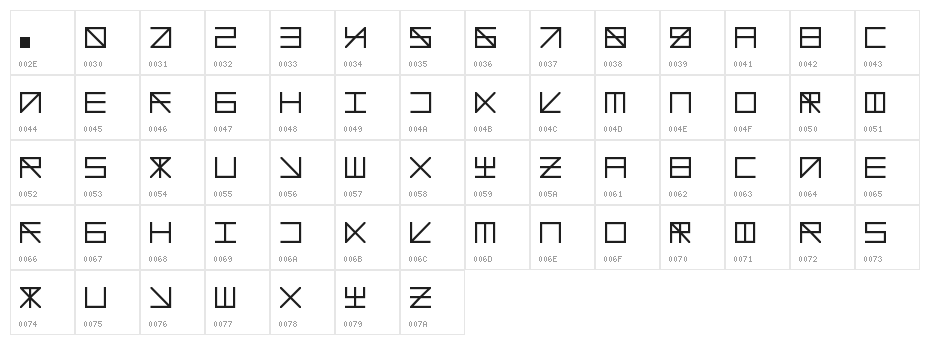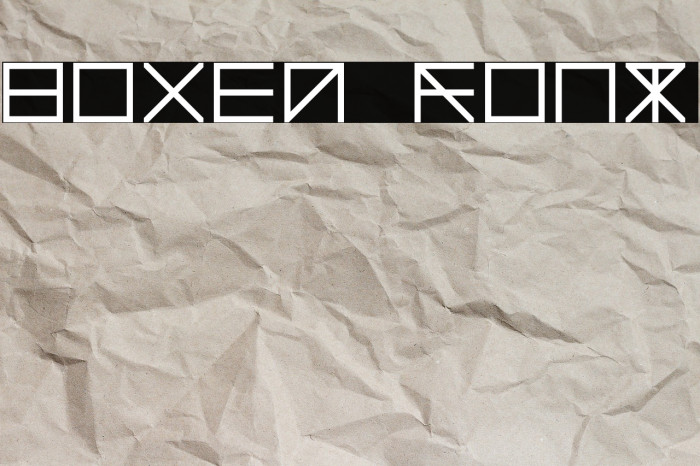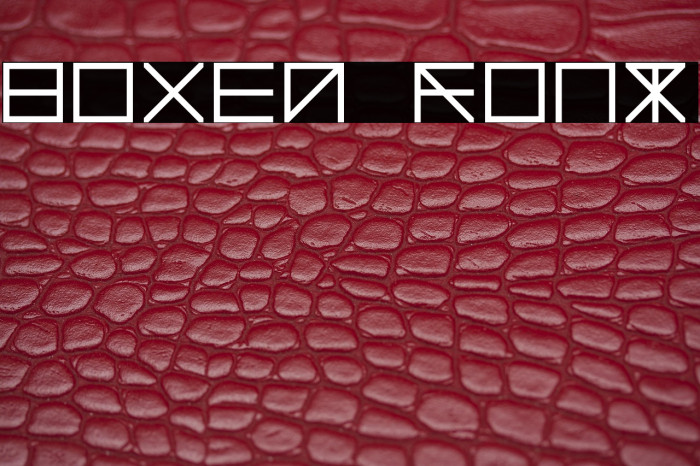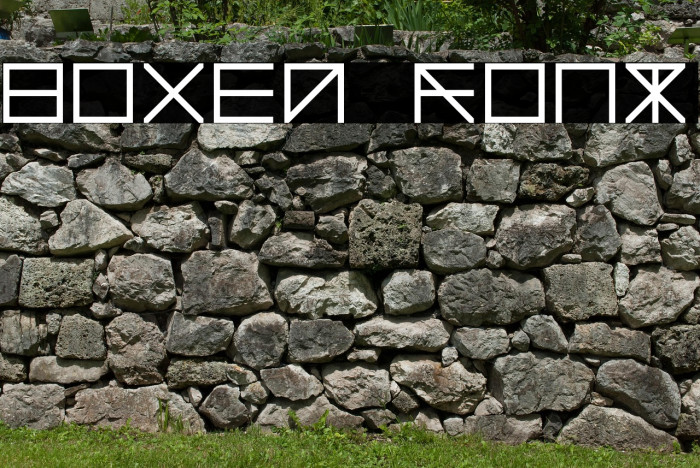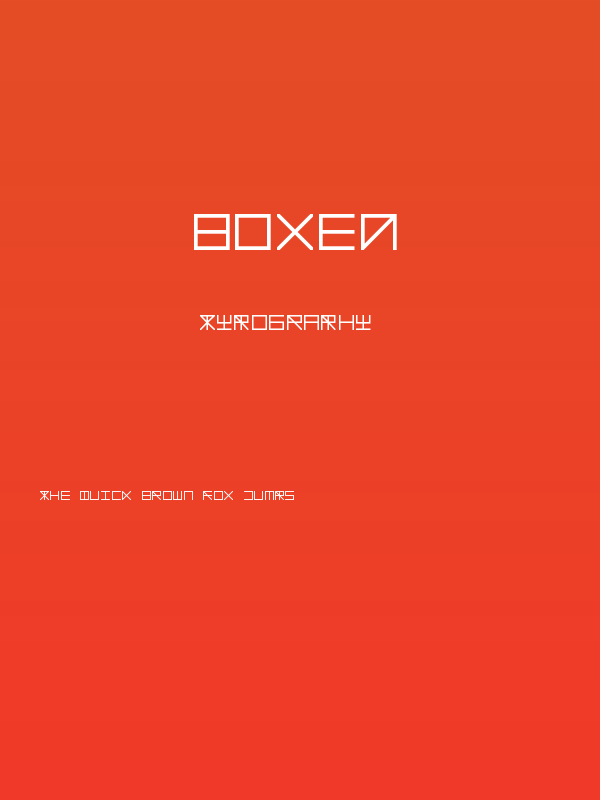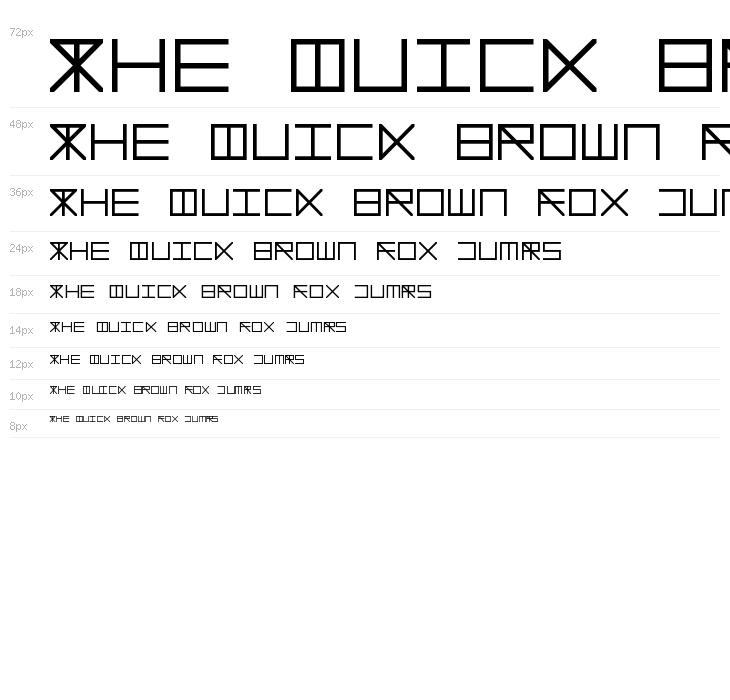
Boxed Font
| Caso de uso | Logos, Headlines, Posters |
| Proyectos propuestos | Ideal for technology branding, sci-fi themed designs, modern posters, and digital interfaces. |